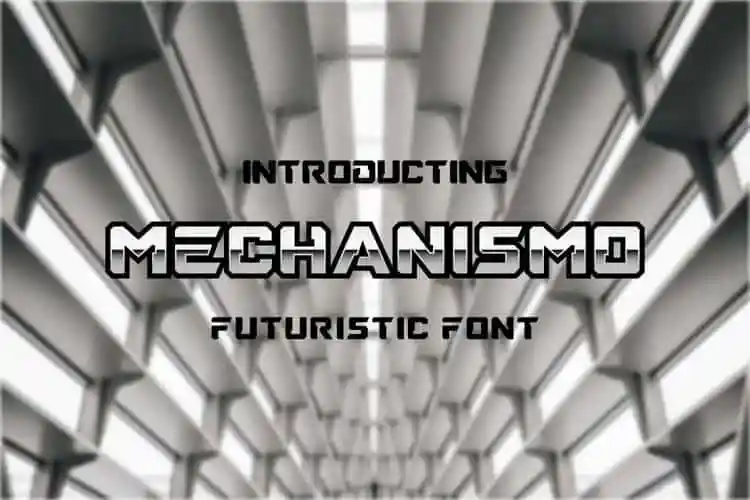
Mechanismo Display Font
Esta fonte ‘Mechanismo Display Font’ traz uma aparência moderna e interessante que se destaca para diversas iniciativas e promoções. Ela carrega o estilo futurista do SF, com formas únicas tanto no alfabeto maiúsculo quanto minúsculo. Ideal para designers em busca de algo único e atemporal, esta fonte se adapta perfeitamente a diversos projetos digitais modernos. Suas linhas clean e seu design minimalista contrastam elegantemente com os materiais visuais mais tradicionais ou vibrantes que podem ser usados nela, criando um impacto visual notável e único. Engane-se em pensar apenas na tecnologia quando vê a fonte ‘Mechanismo Display Font’; suas formas futuristas também têm uma forte influência artística, tornando-a perfeita para aplicações que valorizam uma combinação de estética minimalista com um toque de criatividade.